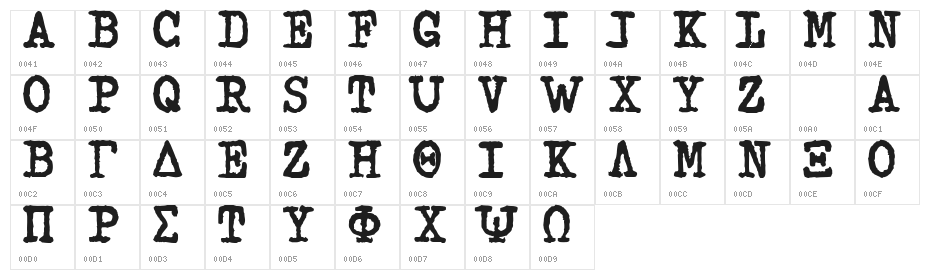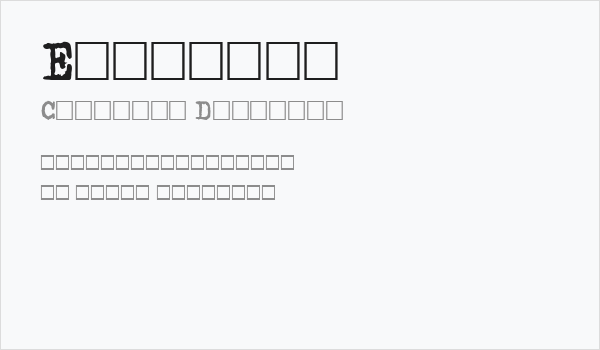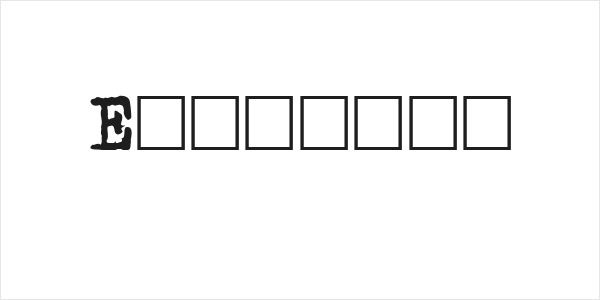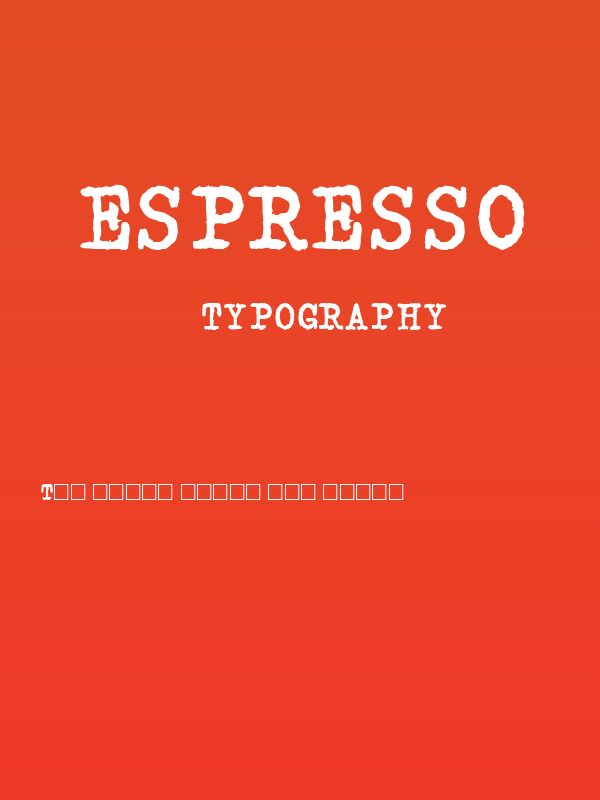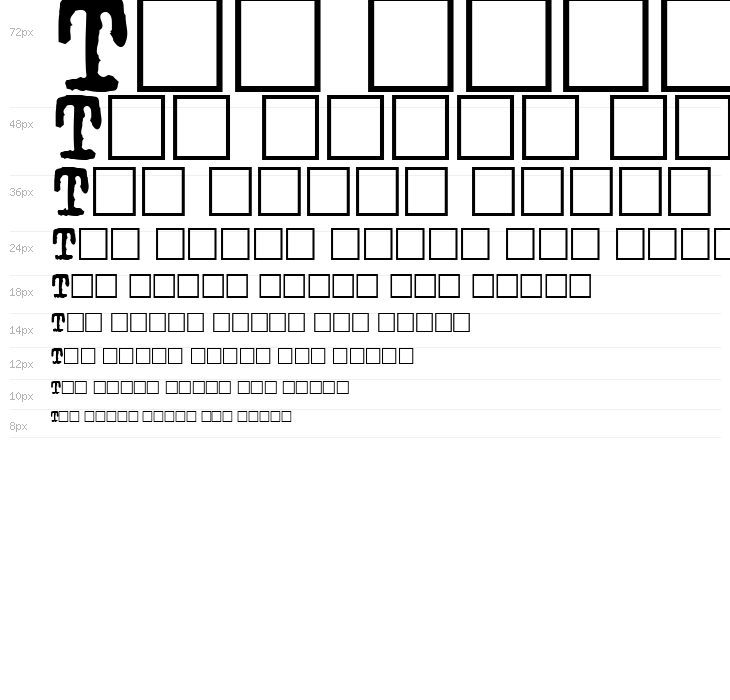
Espresso Font
✎ Typewriter
| Kategorien | Typewriter |
| Gesamtstil | Vintage |
| Vorgeschlagene Projekte | Ideal for vintage posters, branding for rustic or industrial-themed businesses, and designs that require a handcrafted or nostalgic touch. |